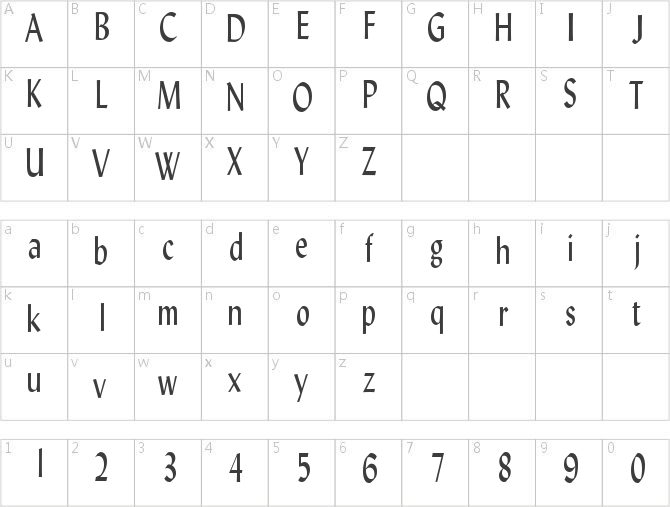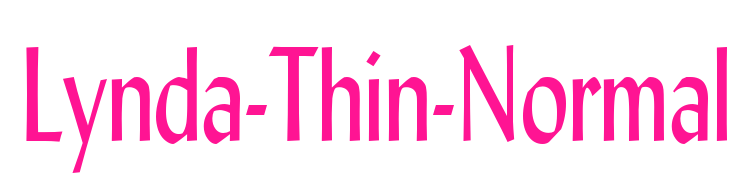
Lynda-Thin-Normal 詳情頁
字體名稱: Lynda-T
Lynda-Thin-Normal
Lynda-Thin-Normal介紹
Lynda-Thin-Normal字體字庫是一款讓人賞心悅目、百看不厭的英文字體,適合各類廣告和產品包裝設計應用,字體大小0.04MB,格式為ttf字體,上傳用戶是速拓科技,作者/版權方為未知